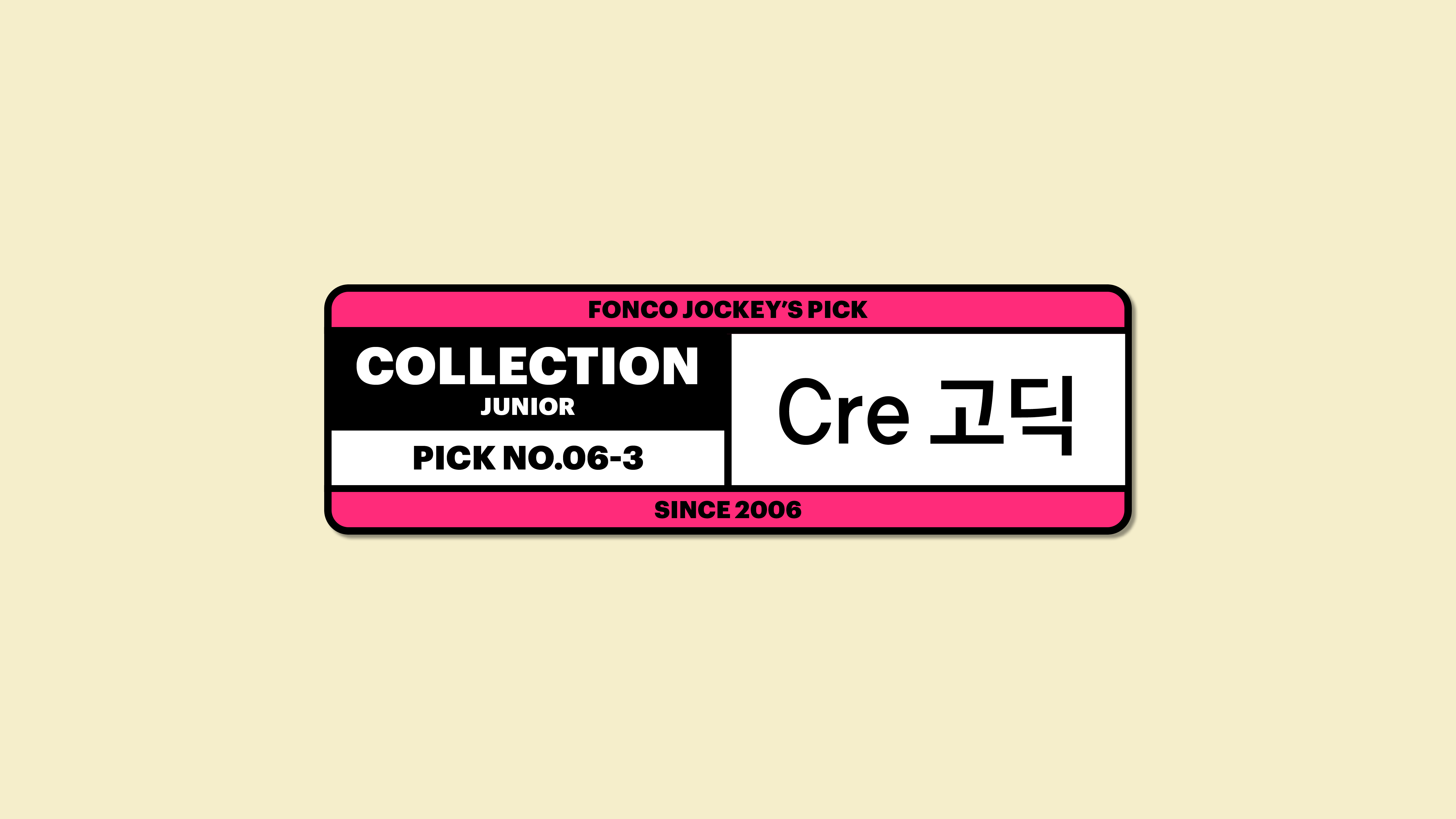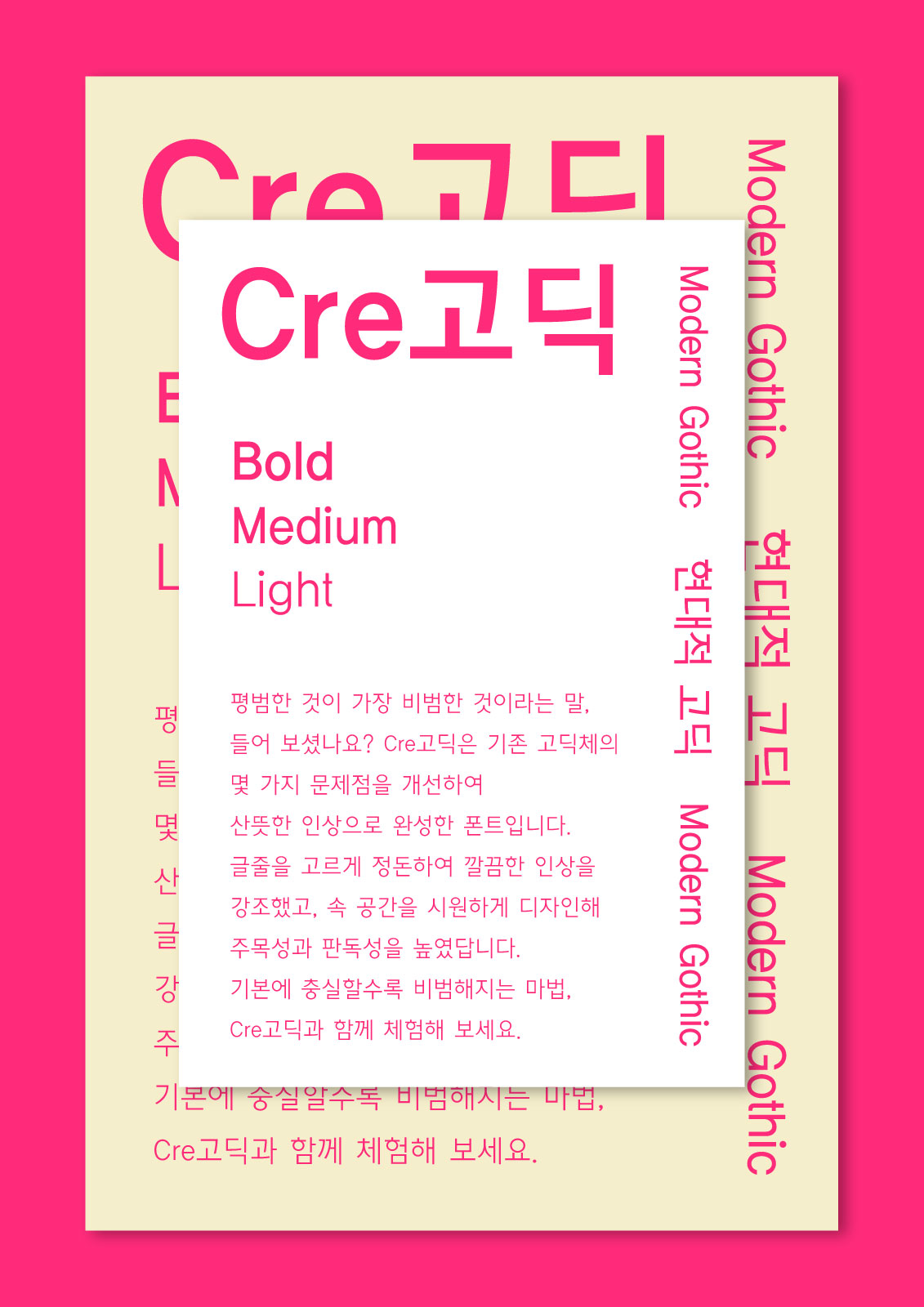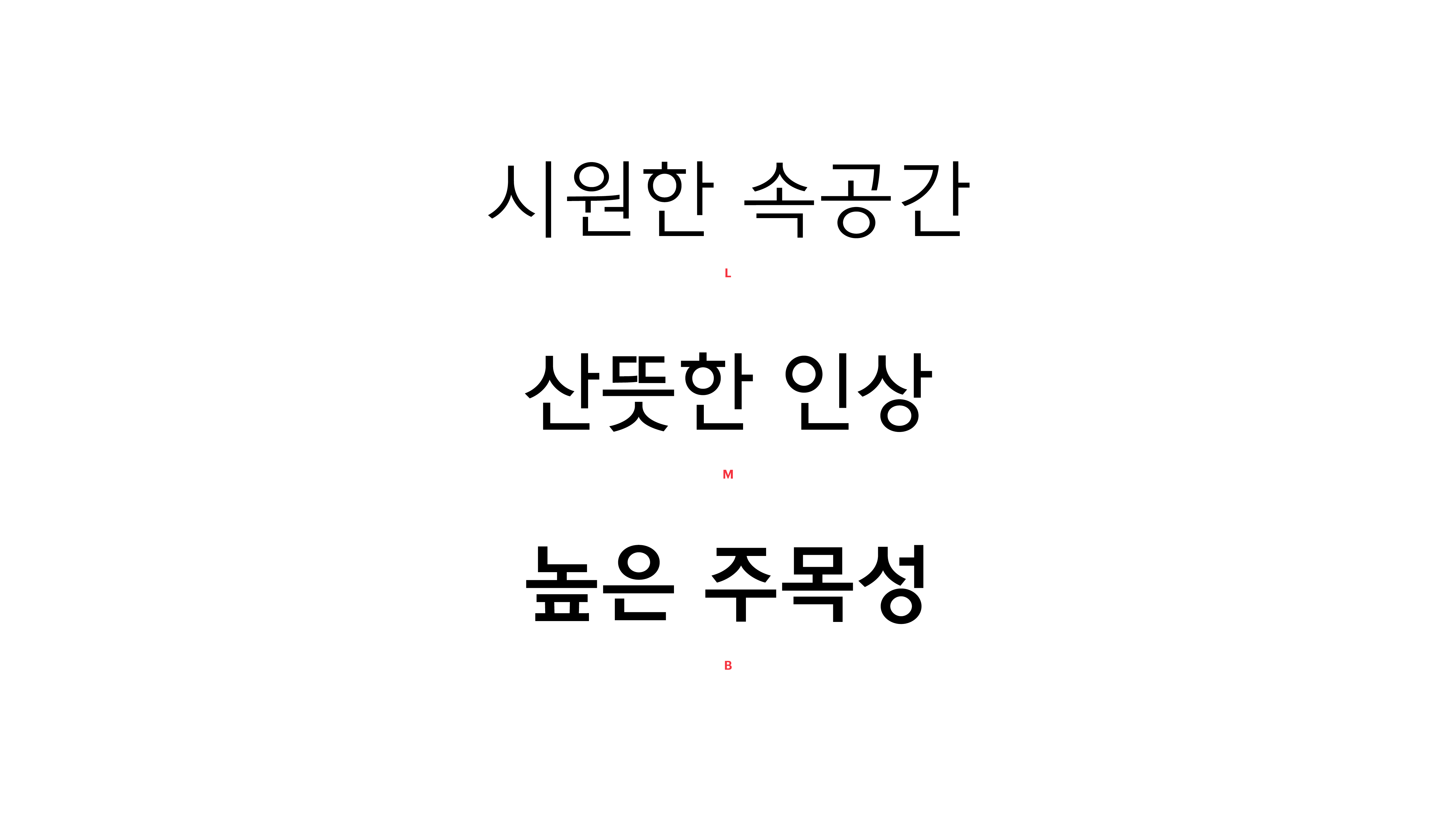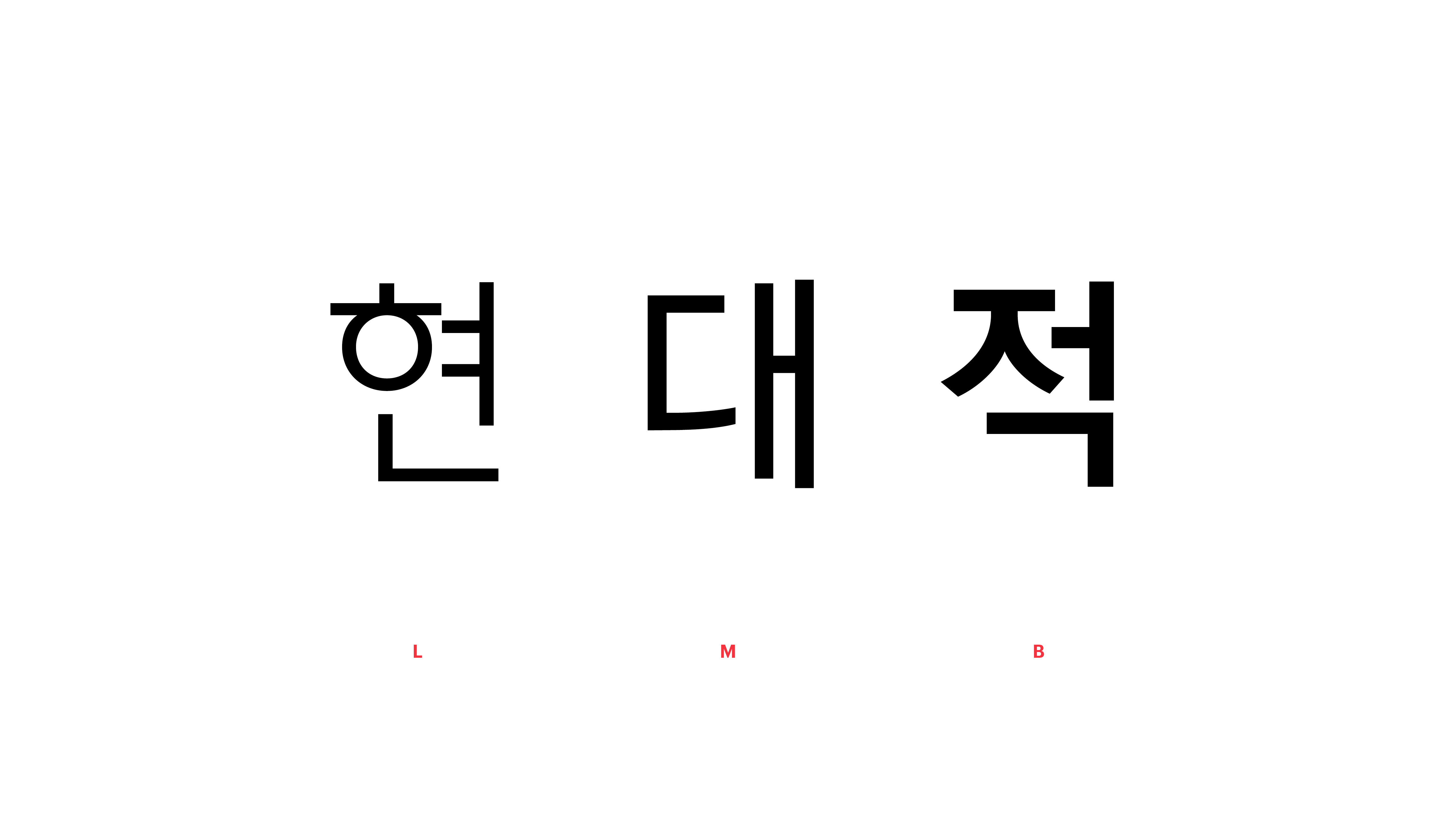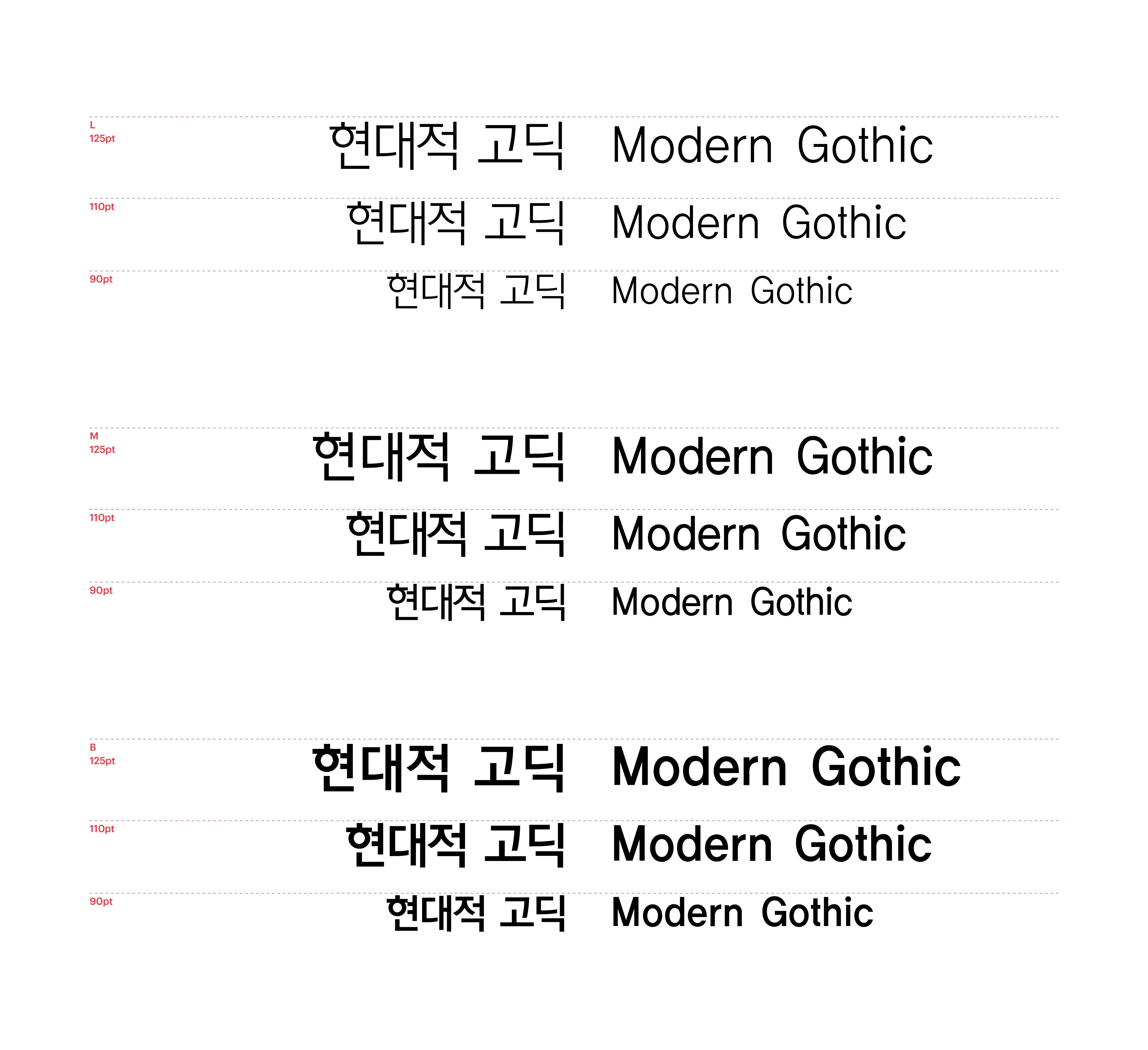
Cre고딕
Yoon Cre고딕
평범한 것이 가장 비범한 것이라는 말, 들어 보셨나요? Cre고딕은 기존 고딕체의 몇 가지 문제점을 개선하여 산뜻한 인상으로 완성한 폰트입니다. 글줄을 고르게 정돈하여 깔끔한 인상을 강조했고, 속 공간을 시원하게 디자인해 주목성과 판독성을 높였답니다. 기본에 충실할수록 비범해지는 마법, Cre고딕과 함께 체험해 보세요.